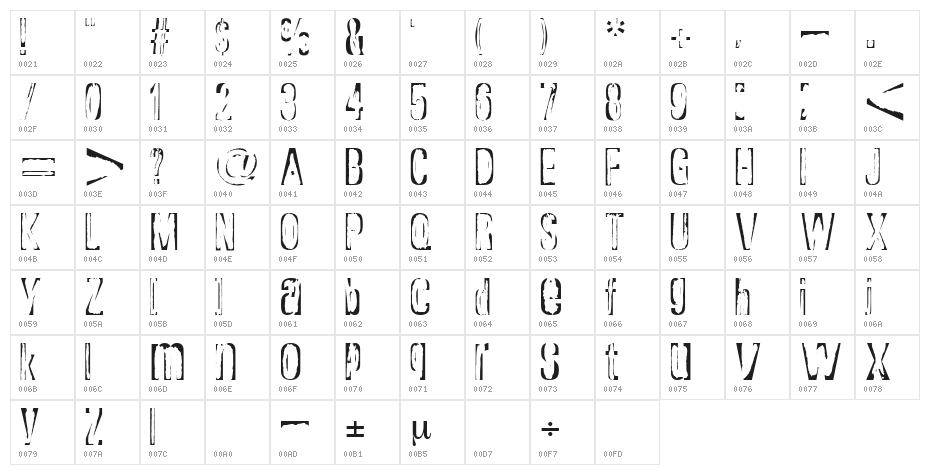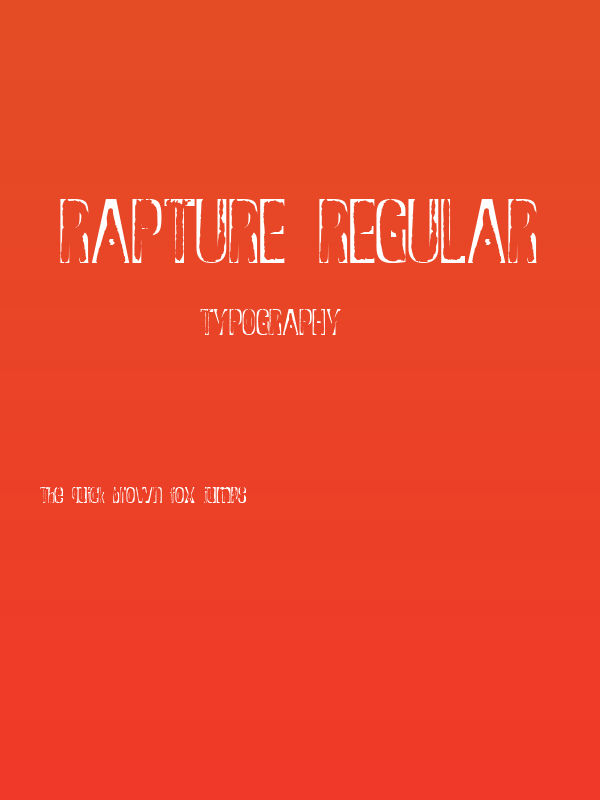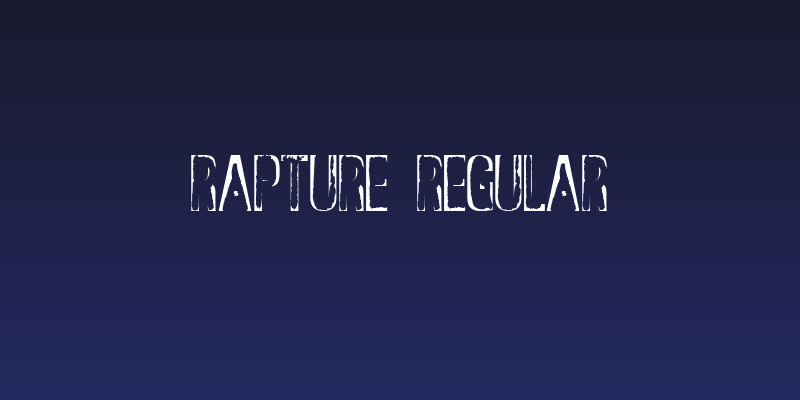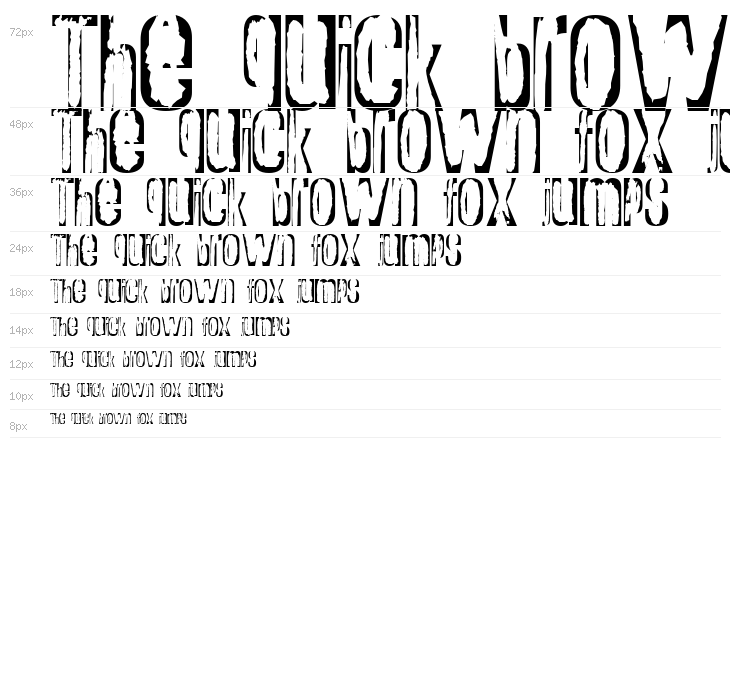
Rapture Regular Font
✎ Distorted Eroded
| Kategorien | Distorted Eroded |
| Gesamtstil | Vintage |
| Vorgeschlagene Projekte | Ideal for projects requiring a vintage or rugged look, such as album covers, posters, or branding for outdoor or adventure-themed products. |